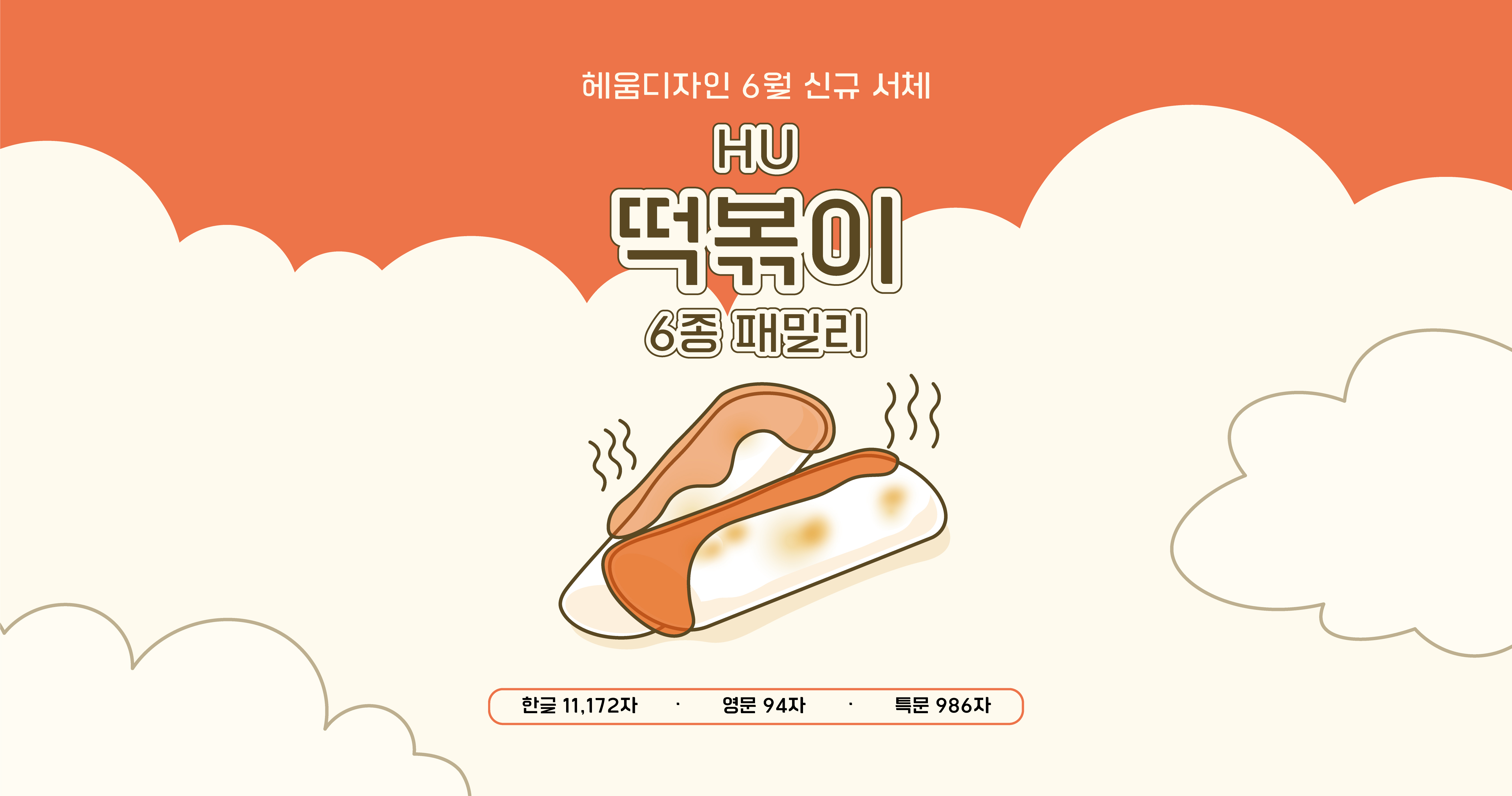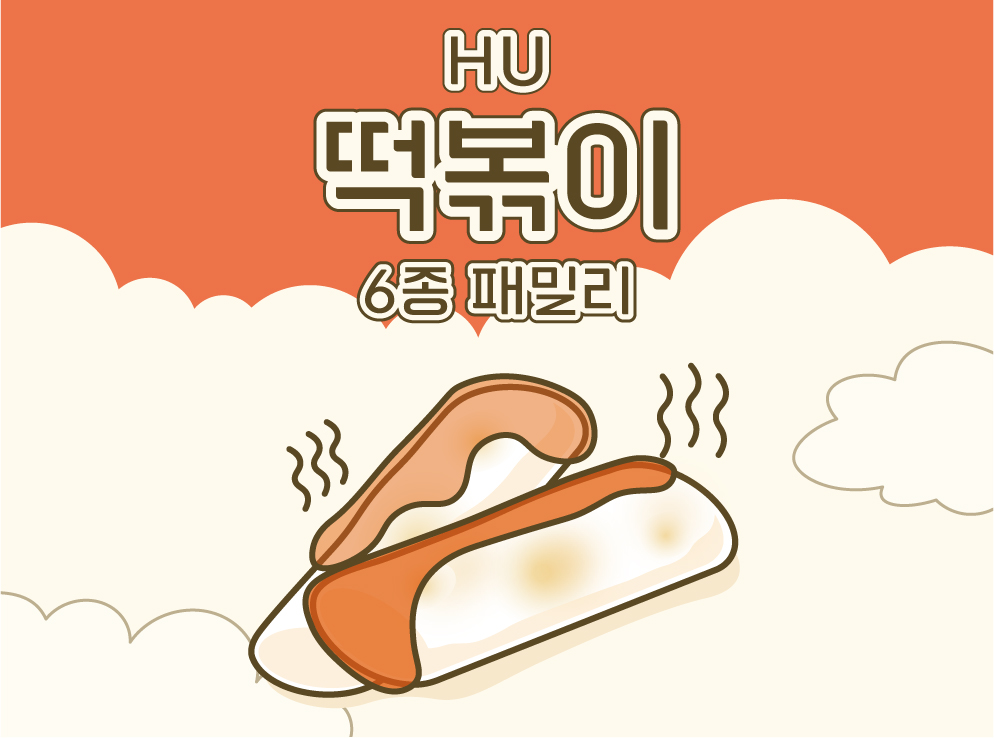
직선적인 획과 끝을 둥글게 표현하여 가래떡 느낌이 나는 귀여운 헤드라인 서체입니다.
초성과 종성의 ‘ㄹ’은 다르게 디자인하여 재밌는 리듬감과 곧게 뻗은 획들과 생동감 있는 곡선으로 글씨의 개성을 더했습니다.
폰트 HU떡볶이 패밀리
굵기 6종
* Light
* Regular
* Medium
* SemiBold
* Bold
* ExtraBold
구성 KS한글 11,172자